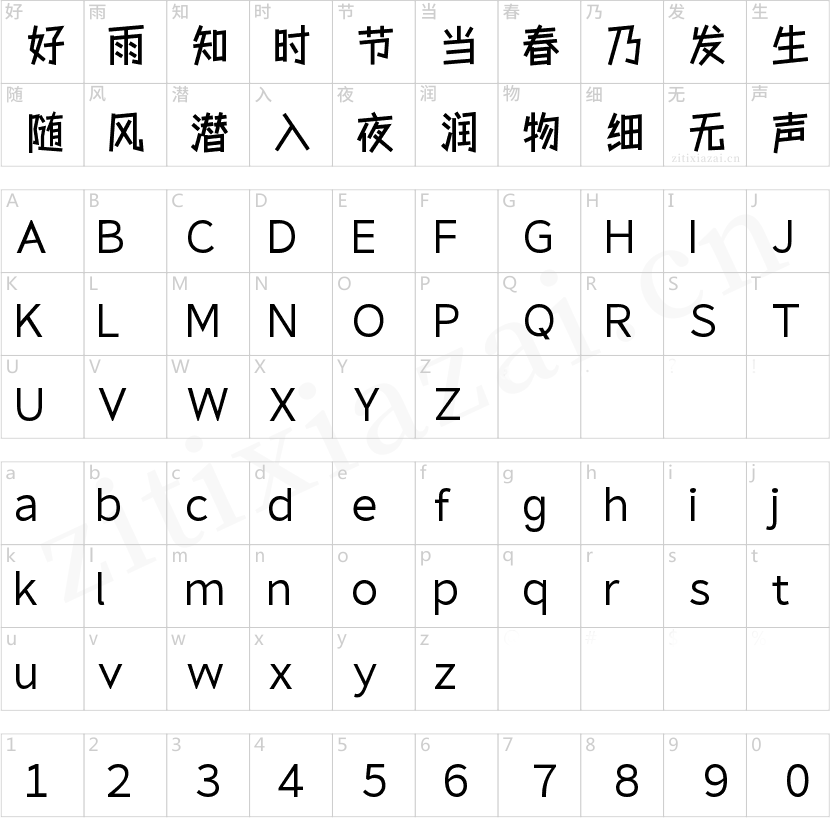
壹心趣玩体
壹心趣玩体,这款字体结构工整、笔画清晰,兼顾美观与易读性,适用于标题、正文、海报、包装、LOGO 等多种场景。字形优雅稳定,风格百搭耐看,适配日常排版与创意设计,让文字呈现更舒适、更具质感。壹心趣玩体一笔一画,皆是细节,以均衡的比例、流畅的线条打造舒适视觉体验,字形端正大气,风格简约现代。无论是商业设计、品牌宣传还是日常排版,都能轻松驾驭,让文字更有格调与力量。壹心趣玩体字体下载。